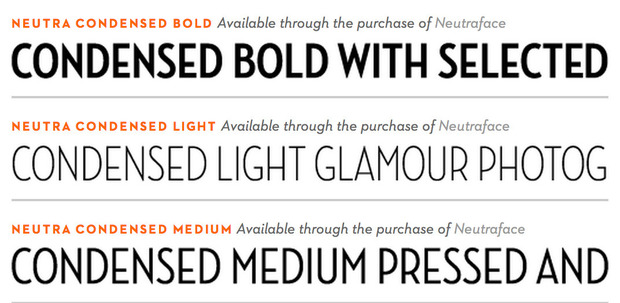
10 font per architetti
Qualcosa ti disturba nell'impaginazione di un elaborato e nella lettura di un pannello informativo? Perdi ore nella scelta e nell'abbinamento di font per tavole di concorso o per il tuo portfolio? Non preoccuparti, non sei certo l’unico: è una delle più comuni ossessioni di architetti e designer! Una lista di 10 font per architetti ti aiuterà nella scelta dei caratteri per layout di concorso, booklet e dettagli tecnici.
La tipografia, con l’insieme dei font, pesi e colori, aiuta a schematizzare e rendere più chiara la comunicazione di tutti i progetti grafici. Nelle tavole di concorso sono sicuramente le immagini a svolgere il ruolo principale, ma non bisogna sottovalutare l’importanza del testo. Una scelta sbagliata può pregiudicare l’esito dell’intera composizione, mentre la gerarchia e leggibilità dei caratteri veicolano un messaggio coerente e lineare.
EMBT Benedetta Tagliabue, Ampliamento della Scuola di Musica per la Gioventù, Amburgo, 2011
La maggior parte degli architetti, anche senza alcuna cognizione del lettering e del graphic design, utilizza caratteri sans serif, cioè senza grazie, perché minimal, neutrali e più chiari a monitor. Altri, come Miralles Tagliabue EMBT, Carme Pinós e Frank Lloyd Wright, hanno definito una propria identità tipografica coniando caratteri in linea con il proprio stile e la personalità architettonica.
Di seguito una collezione di font per architetti (la maggior parte gratuiti e sans serif) con alcune curiosità sulle origini, da combinare con uno, massimo due, più esuberanti e in contrasto.
10 font per architetti e designer
Il font Avenir
Avenir significa "futuro" in francese e si ispira infatti al font Futura, ma appare meno geometrico e razionale. Questo font, adatto agli elaborati grafici degli architetti per la sua semplicità, risale al 1988, ed è stato elaborato dal più noto e prolifico tipografo del XX secolo Adrian Frutiger, che oltre all’Avenir, ha creato l’Univers e il Frutiger. Tutti accumunati da un’estrema leggibilità e linearità, sono font immortali e molto utilizzati in vari ambiti. Alla già ricca e variegata famiglia Avenir è stata aggiunta nel 2003 la collezione Next Pro, ideata dal giapponese Akira Kobayashi. Menzione particolare merita l’Avenir Next Condensed (il font prediletto di mia sorella!); elegante e sottile si sposa perfettamente con i serif tradizionali come Minion, progettato da Robert Slimbach per l’Adobe.
Il font Courier New
Era il tipo di carattere della maggior parte delle macchine da scrivere e per questo un font che gli architetti che vogliono dare un tocco retrò ai propri elaborati grafici. E' anche molto utilizzato nella programmazione, perché monospazio e slab serif, ovvero con minima o nessuna differenza di spessore tra le aste, le grazie ben marcate e perpendicolari. Lo stile del carattere Courier è stato progettato nel 1955 da Howard Kettler: in principio avrebbe voluto chiamarlo "Messenger" (messaggio), ma poi decise per Courier (corriere), conferendogli un significato più nobile.
Il font Eaglefeather
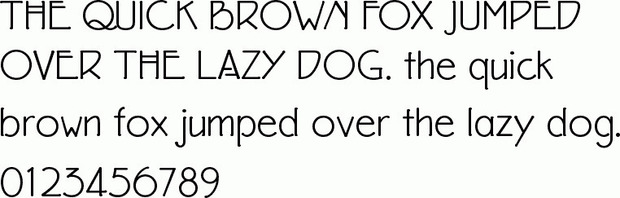
È il font disegnato e utilizzato dall'architetto Frank Lloyd Wright, rilasciato in forma digitale nel 1997 grazie al designer David Siegel. Seguendo gli insegnamenti del maestro Louis Sullivan, Wright realizzò elaborati non semplicemente funzionali e esplicativi del progetto architettonico, ma vere e proprie opere d’arte con testi in sintonia agli edifici ideati. Il font Eaglefeather è stato realizzato a partire dai disegni dell’Olive Hill, un complesso di edifici adibiti a centro artistico, ora noto come Barnsdall Park. Wright aveva concepito 19 lettere, tutte maiuscole; Siegel e il designer Carol Toriumi-Lawrence, hanno successivamente completato l’alfabeto e tutti caratteri minuscoli in linea con gli originali. Il nome del font deriva da un altro progetto dell’architetto, una casa a Malibù realizzata per il produttore Arch Oboler. È un font molto particolare, con doppia barra per la A e H, la S graziosa e inclinata come una scala mobile, che ricorda la scrittura a mano e il movimento Arts and Crafts a cui Wright rimase fedele.
Il font Futura
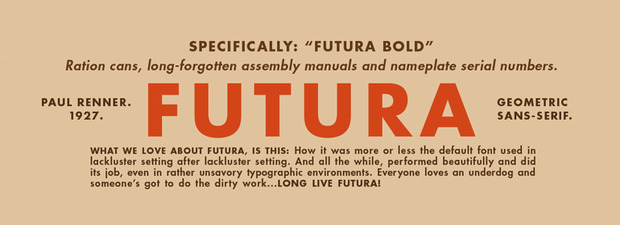
Il font si ispira alla Bauhaus e fu sviluppato dal designer tedesco Paul Renner nel 1927. Può essere considerato il padre di tutti i font dell’architettura e dei sans serif geometrici, caratterizzato da una sobria sintonia tra curve e linee dritte. Progettato a partire da forme pure, quali quadrati, cerchi e triangoli, è leggibile e facilmente individuabile a qualsiasi scala, utilizzato largamente nella cultura popolare. Brand famosi, Ikea, Absolut e Red Bull, e grandi artisti come il regista Stanley Kubrick, hanno scelto il font Futura perchè affascinati dalla sua forte personalità che ben si adatta a titoli, headlines e testi in maiuscole.
Il font Gill Sans
Il nome del carattere viene dal suo inventore, l’incisore Eric Gill, che forgiò tantissimi altri caratteri tra cui Perpetua e Joanna. È un font versatile, decoroso ma senza grazie, il più british che esista, utilizzato per i loghi e le grafiche della BBC, la chiesa d’Inghilterra e la British Railways. La versione light è sicuramente la più adatta in ambito architettonico.
Il font Gotham
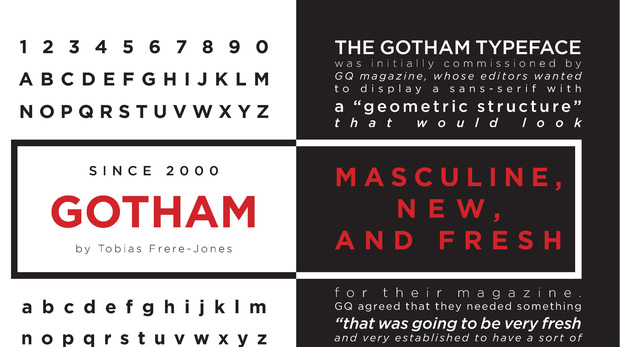
Soprattutto utilizzato in maiuscolo, è un font molto discreto e onesto. Nato dalla mano di Tobias Frere-Jones per la Hoefler Frere-Johnson di New York nel 2000, si è diffuso notevolmente grazie alla ricchezza e varietà della sua famiglia (40 diversi pesi, dal light all’ultra). È stato utilizzato dalla campagna presidenziale di Obama e per la locandina del film "Gran Torino" di Clint Eastwood.
Il font Helvetica
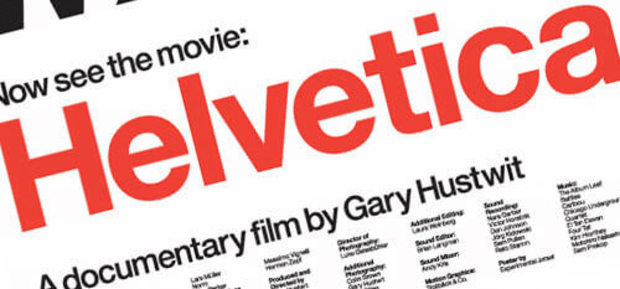
Nato nel 1957 in Svizzera, come suggerisce il nome, da Max Miedinger e Eduard Hoffman per la fonderia Haas di Munchenstein a Basilea. Negli anni Sessanta diventò famoso in tutte le sue versioni (light, bold e italic) grazie a campagne pubblicitarie e addirittura il protagonista del film "Helvetica" di Gary Hustwit. Bellissimo font, tondo, deciso ma forse un po’ troppo visto.
Il font Ostrich Sans
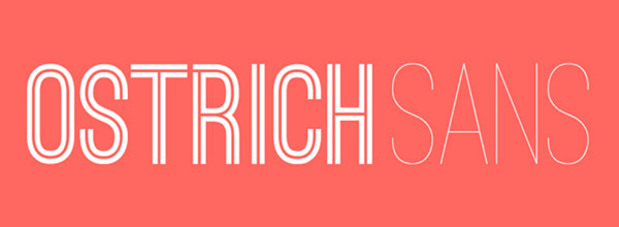
È un font recente, disegnato da Tyler Finck nel 2011, che lo definisce un favoloso sans serif dalle estremità allungate. Molto elegante, sottile e adatto per titoli e testi in lettere maiuscole.